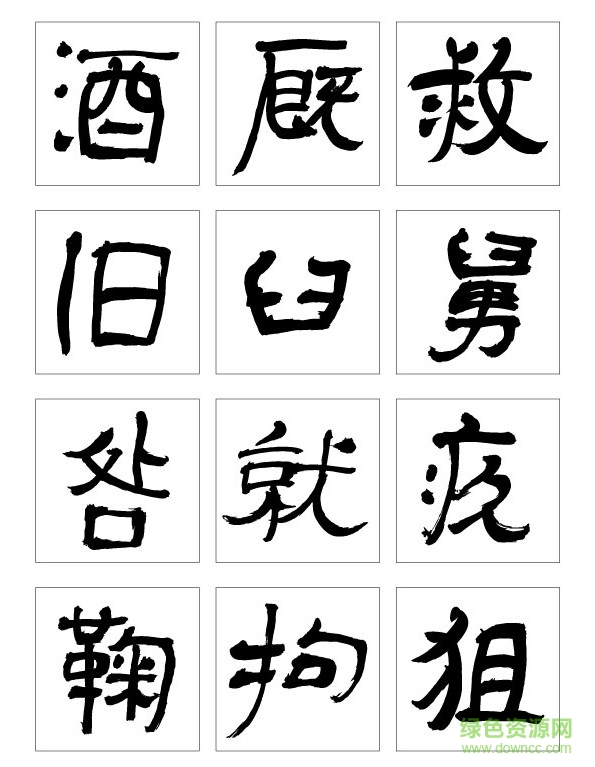
方正彥辰清酒簡體是彥辰字體中非?;馃岬囊豢钭煮w,李佛君先生精心創(chuàng)辦的這款字體深受大眾的喜愛。有興趣的朋友趕快來綠色資源網(wǎng)下載吧!
方正彥辰清酒簡體是由彥辰設(shè)計(jì)李佛君的作品,全球最大中文字體系統(tǒng)--北京北大方正簽約字體設(shè)計(jì)師,字體作品有“方正彥辰清酒體“及”方正佛君包裝體”
字體設(shè)計(jì)常常需要取材傳統(tǒng)書法,難點(diǎn)就在如何集萃歷史上代表性書法家的書作精華,根據(jù)印刷技術(shù)和平面設(shè)計(jì)的需求與運(yùn)用特點(diǎn),將其與現(xiàn)代造字技術(shù)結(jié)合?!皬┏綒W楷”的設(shè)計(jì)師將各代的習(xí)歐、寫歐書法家作品融合,去除書寫習(xí)氣,賦予其現(xiàn)代平整與規(guī)律性的美感,形成具有時(shí)代新意的書法字形,使其在保持疏朗空靈的傳統(tǒng)風(fēng)格的同時(shí),具備識(shí)別性和印刷的規(guī)范性。